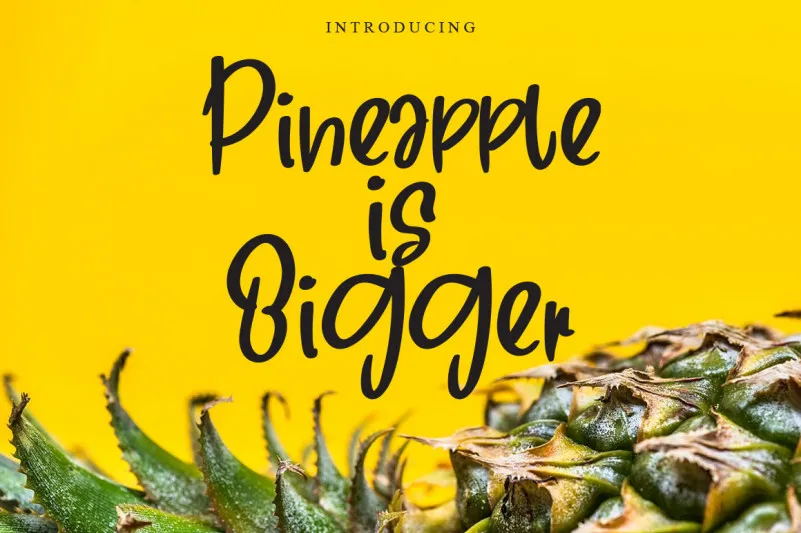
Esta fonte é um delicado script criado com elegância para quem busca algo que se destaque em qualquer projeto. Seja para criar posts bonitos no Instagram ou para trazer um toque artesanal e autêntico às suas criações de DIY, essa fonte transformará qualquer ideia criativa em arte verdadeira. Com uma textura única e graciosidade, ela é perfeita para quem busca algo que se destaque na web ou no ambiente físico dos seus projetos. Ideal para designers, ilustradores e amantes do bom design, a Pineapple in Bigger Font oferece um toque de personalização especial. Seja em uma frase de boas-vindas, num cartão de visita ou até mesmo nas suas próprias letras digitais customizadas, essa fonte traz brilho à sua produção. Esse script é perfeito para quem busca algo comum mas diferente. Com texturas suaves e linhas delicadas, ela consegue dar um toque especial a qualquer obra de arte digital ou impressa que você quiser criar. Como uma amiga fiel do seu trabalho, essa fonte estará sempre pronta para ajudar a torná-lo único.